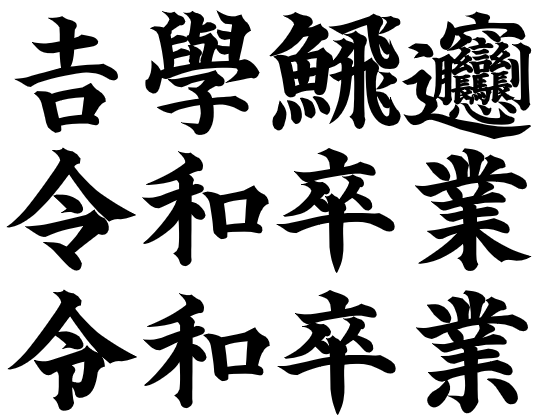
武蔵賞状楷書体
このサンプルは「太」で作成
概要
• 賞状用にデザインした毛筆楷書体フォントですが、宛名書き用など幅広くご利用できます。
• 漢字を約15,560文字、ひらがな・カタカナ・アルファベット・記号などを約1,400文字、合計約16,960文字収録しています。
• 太さに応じて、通常、太、極太の3種類あります。太さの違いは任意文字のサンプル文字一覧でのサンプルでご確認ください。
• 学習指導要領に準拠した字形です。そのため小中学校でもご利用いただけます。
• 糸偏などの書式を変えたフォント(書体名の後ろに「匠」が追加されます)も付属します。字形の詳細は武蔵賞状楷書体匠についてをご覧ください
• 人名用漢字・外字を搭載しています(下記の「特徴」を参照)。
• Unicode IVSに対応しています(下記の「特徴」を参照)。
• JIS新規格(JIS X 0213:2004、単にJIS2004とも呼ばれる)に対応した字形です。旧規格の字形はUnicode IVSの異体字、または外字領域に収録してあります。
新規格と旧規格の字形の違いについてはJIS旧規格と新規格の違いをご参照ください。
特徴
Ver3.00で大幅に漢字を追加
Ver3.00で漢字を5,075文字、Ver3.10で約1,010文字、Ver4.00で約1,200文字追加し、合計約16,960文字になりました。
法務省制定 人名用漢字を全て収録
法務省が制定している人名用漢字を全て内字領域に収録しています。
Unicode IVSに対応
Unicode IVSに対応した異体字を約1,350字収録しています。
Unicode IVSの異体字を使うにはマイクロソフト WordなどのUnicode IVSに対応したアプリが必要ですが、外字領域にも同じ異体字を収録しているため、Unicode IVSに対応していないアプリでも外字として表示できます。
人名用などの外字を収録
上記 Unicode IVSの他に、外字領域に人名用などの外字を395文字収録しています。